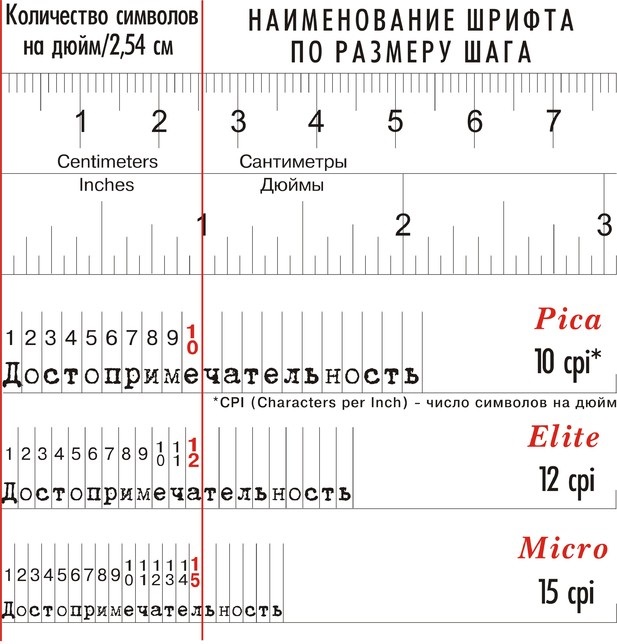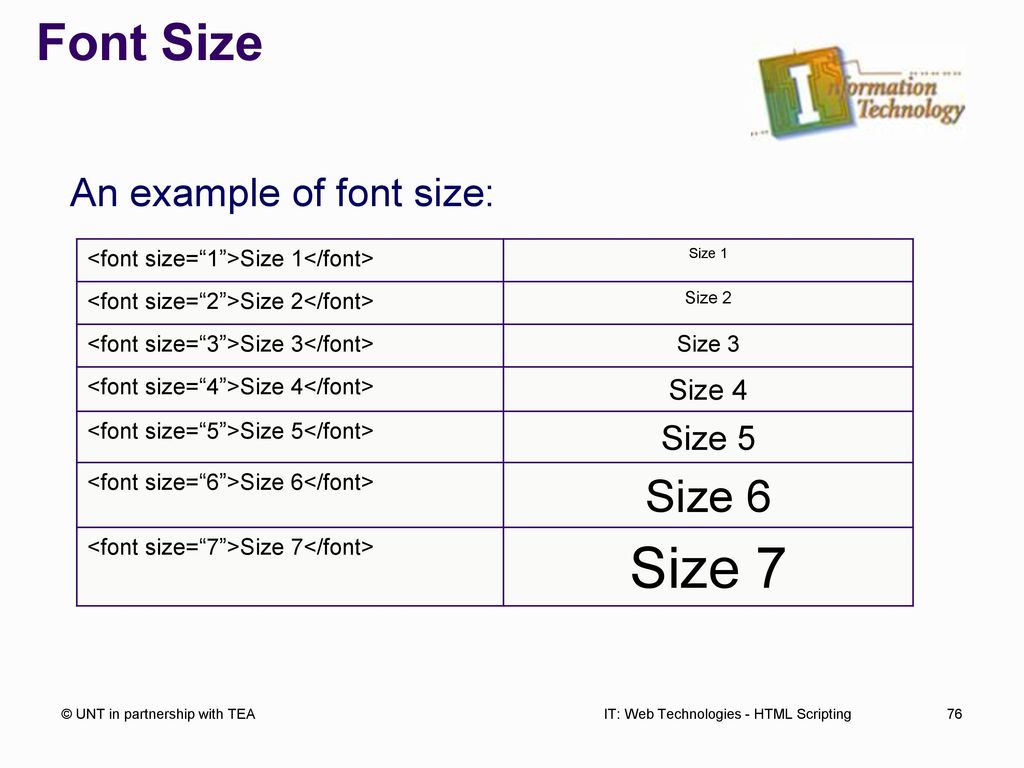
Гарнитура шрифтов, размер и основные параметры. Параметры шрифта Что определяет размер шрифта
Пика равна 12 пунктам,что чуть меньше 1/6 дюйма (большинство людей округляет эту величину). Ширина и высота колонок и полос выражаются в пиках.
Пункт составляет 0,353 мм. Размер шрифта и расстояние между строками оценивают в пунктах.
Цицеро-это единица, принятая в большинстве стран Европы. Она примерно равна пике (5,62 цицеро равны 1 дюйму).
Термины круглая шпация, полукруглая шпация тонкая шпация характеризуют горизонтальные размеры шрифта. Они соответствуют ширине заглавных букв М, N и строчной буквы t.
Круглая шпация равна размеру шрифта, полукруглая шпация составляет 0,5 размера
шрифта, а тонкая шпация — 0,25 размера шрифта. Другими словами, для 12-пунктового
шрифта круглая шпация равна 12 пунктам, полукруглая шпация — 6 пунктам,
а тонкая шпация — 3 пунктам. Ширина цифры показывает, сколько места на
строке занимает цифра. Она равна полукруглой шпации (в большинстве шрифтов
все цифры имеют одинаковую ширину, что особенно удобно при формировании числовых
колонок в таблицах).
В следующей таблице приведены соотношения основных единиц измерения:
ОСНОВНЫЕ ТЕРМИНЫ
ШРИФТ
Шрифт-это набор символов определенного размера и рисунка (например, полужирный шрифт New Baskerville размером 10 пунктов).
Большую часть шрифтов можно разделить на четыре группы: шрифты с засечками, или антиква (serif), шрифты без засечек, или гротески (sans serif), декоративные (decorative) и рукописные (script).
Ниже приведены образцы некоторых широко распространенных в DTP шрифтов:
ГРУППЫ ШРИФТОВ
Для каждого шрифта существует несколько вариантов начертания: нормальное (plain), курсивное (italic), жирное (bold) и жирное курсивное (bold italic). Различные варианты начертания некоторого шрифта всех возможных размеров (кеглей) объединяются в одно шрифтовое семейство или гарнитуру.
Ниже приведен пример различных начертаний гарнитуры Таймс:
Times Plain
Times Italic
Times Bold
Times Bold Italic
Конечно, это далеко не все возможные начертания, однако эти начертания обязательно
присутствуют во всех гарнитурах.
Кроме них можно назвать такие широко распространенные
начертания, как: светлое (light), суперсветлое (extra light), полужирное (demi
bold), супержирное (extra bold), сжатое (compressed или condensed). Существует
и множество других, для которых иногда даже нет общепринятого наименования.
ПРОПОРЦИИ ШРИФТА
В зависимости от пропорций знаков шрифт может быть сжатым (condenced), нормальным (normal) и широким (expanded). Реализация сжатого шрифта некоторой гарнитуры как отдельной разновидности в DTP-системах скорее исключение, чем правило. В подавляющем большинстве сжатые шрифты получаются средствами самой DTP-системы — путем пропорциональной деформации. Причем такая деформация может представлять собой не обязательно сжатие — строятся и растянутые начертания.
ОФОРМИТЕЛЬСКИЕ ЭФФЕКТЫ
Одной из интересных возможностей оформления любых шрифтов является построение
контурных литер (Outline-эффект). В DTP-системах реализована также возможность
создания теневого (Shadow) эффекта для любых шрифтов.
Эти и многие другие эффекты реализуются компьютером путем модификации стандартных шрифтов по определенным алгоритмам.
Среди других, часто используемых оформительских операций, можно назвать следующие: подчеркивание и двойное подчеркивание, перечеркивание, смещение текста относительно нормального положения строки и разнообразные их комбинации.
РАЗМЕР ШРИФТА
Размером шрифта называется расстояние между верхней и нижней шрифтовыми линиями. Обычно размер шрифта (кегль) выражается в пунктах.
Визуальное определение размера шрифта представляет сложность только для начинающих пользователей DTP-систем. Даже после непродолжительной работы пользователь приобретает опыт и через некоторое время распознает практически безошибочно большинство кеглей часто используемых гарнитур.
На следующей иллюстрации изображены несколько кеглей одной гарнитуры:
Существуют специфические наименования для отдельных кеглей, также «унаследованные
из прошлого»: бриллиант (3 пункта), диамант (4 пункта), перл (5 пунктов),
нонпарель (6 пунктов), миньон (7 пунктов), петит (8 пунктов), боргес (9 пунктов),
корпус (10 пунктов), цицеро (12 пунктов), миттель (14 пунктов), терция (16
пунктов), текст (20 пунктов).
ЕМКОСТЬ И НАСЫЩЕННОСТЬ ШРИФТА
Каждый шрифт имеет свой общий тон или насыщенность — чисто визульный параметр, который характеризует, как будет выглядеть конкретный шрифт на странице. Он может быть светлым или темным. Насыщенность меняется в зависимости от вида шрифта и начертания, равномерности расположения текста.
Шрифты одного и того же кегля могут иметь различную емкость, т.е. в одной строке может помещаться различное количество знаков. В некоторых книгах по типографике приводятся таблицы емкости шрифтов для определения среднего количества знаков для разных кеглей в строках различного формата. Я бы не советовал их использовать, т.к. параметры одного и того же шрифта меняются в зависимости от производителя. Более приемлемым способом является самостоятельное определение емкости. Для этого наберите колонку текста и сделайте ее дубликаты для шрифтов, которые вы собираетесь использовать.